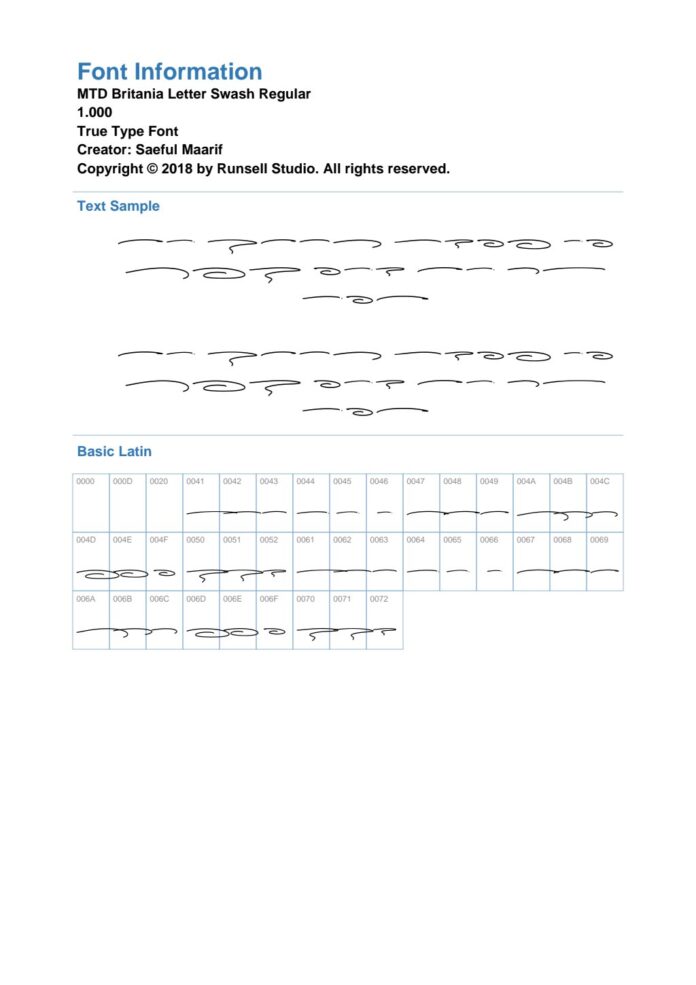
MTD Britania Letter Swash Font Đẹp: Khám phá MTD Britania Letter Swash, phông chữ TrueType tuyệt đẹp với các nét viết tay uyển chuyển và đường cong swash độc đáo. Hoàn hảo cho thiệp mời, logo, và các dự án thiết kế mang phong cách cổ điển, sang trọng.
Giới thiệu về Phông chữ MTD Britania Letter Swash
Trong thế giới thiết kế đồ họa ngày nay, việc lựa chọn một phông chữ phù hợp có thể tạo nên sự khác biệt lớn. MTD Britania Letter Swash nổi bật với khả năng truyền tải cảm giác cổ điển, tinh tế nhưng không kém phần hiện đại và cá tính. Dù bạn là nhà thiết kế chuyên nghiệp hay chỉ đơn giản là người đam mê sáng tạo, phông chữ này chắc chắn sẽ là một công cụ đắc lực để biến ý tưởng thành hiện thực, giúp sản phẩm của bạn thu hút mọi ánh nhìn.
Đặc điểm nổi bật của MTD Britania Letter Swash
MTD Britania Letter Swash không chỉ là một phông chữ, nó là một tuyên ngôn về phong cách và sự tinh tế. Dưới đây là những đặc điểm khiến nó trở thành một lựa chọn không thể bỏ qua:
- Phong cách viết tay sang trọng: Phông chữ này mô phỏng nét viết tay thanh thoát, mềm mại, tạo cảm giác gần gũi, cá nhân và rất nghệ thuật. Nó gợi lên vẻ đẹp cổ điển, lãng mạn của những bức thư tay xưa cũ, nhưng vẫn phù hợp với xu hướng thiết kế hiện đại.
- Ký tự ‘Swash’ độc đáo: Điểm nhấn lớn nhất của MTD Britania Letter Swash là những ký tự ‘swash’ – những đường nét uốn lượn, trang trí mở rộng từ các chữ cái. Những chi tiết này không chỉ làm tăng tính thẩm mỹ mà còn giúp tạo điểm nhấn, biến những dòng chữ đơn giản thành tác phẩm nghệ thuật độc đáo. Bạn có thể sử dụng chúng để tạo ra các tiêu đề nổi bật, chữ ký cá nhân hóa hoặc các họa tiết trang trí tinh xảo.
- Tính dễ đọc: Mặc dù mang phong cách trang trí, MTD Britania Letter Swash vẫn đảm bảo tính dễ đọc cao, đặc biệt khi được sử dụng cho các tiêu đề, slogan, hoặc đoạn văn ngắn. Các ký tự được thiết kế rõ ràng, khoảng cách hợp lý, giúp người đọc dễ dàng tiếp nhận thông tin.
- Tính linh hoạt trong thiết kế: Với sự kết hợp giữa nét cổ điển và hiện đại, phông chữ này phù hợp với nhiều chủ đề và phong cách thiết kế khác nhau. Nó có thể là yếu tố chính tạo nên vẻ đẹp sang trọng, lãng mạn hoặc là điểm nhấn tinh tế cho một thiết kế tối giản.
- Nguồn gốc đáng tin cậy: Được tạo ra bởi Saeful Maarif thuộc Runsell Studio, một cái tên đã được biết đến trong giới thiết kế, bạn có thể tin tưởng vào chất lượng và sự chăm chút trong từng chi tiết của phông chữ này.